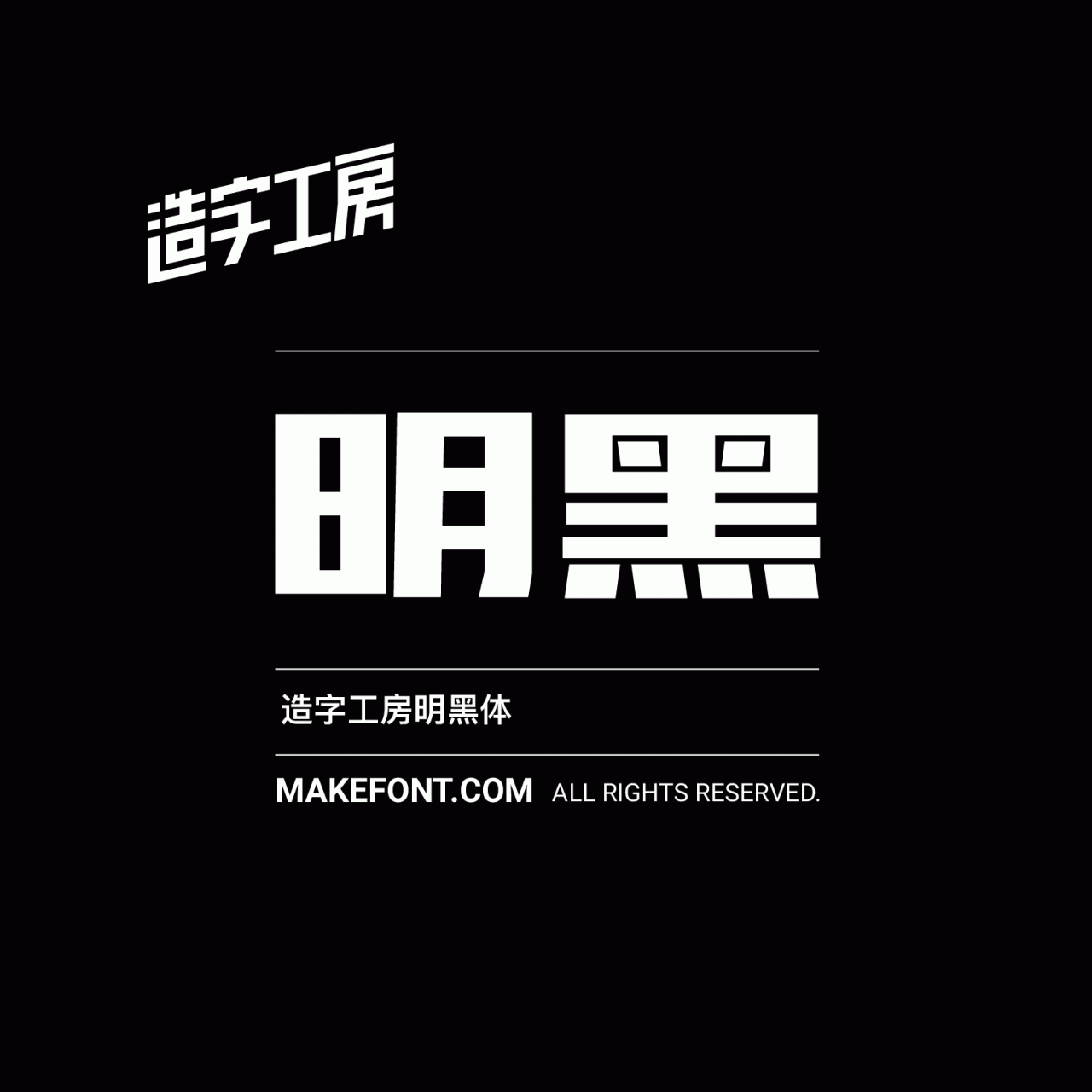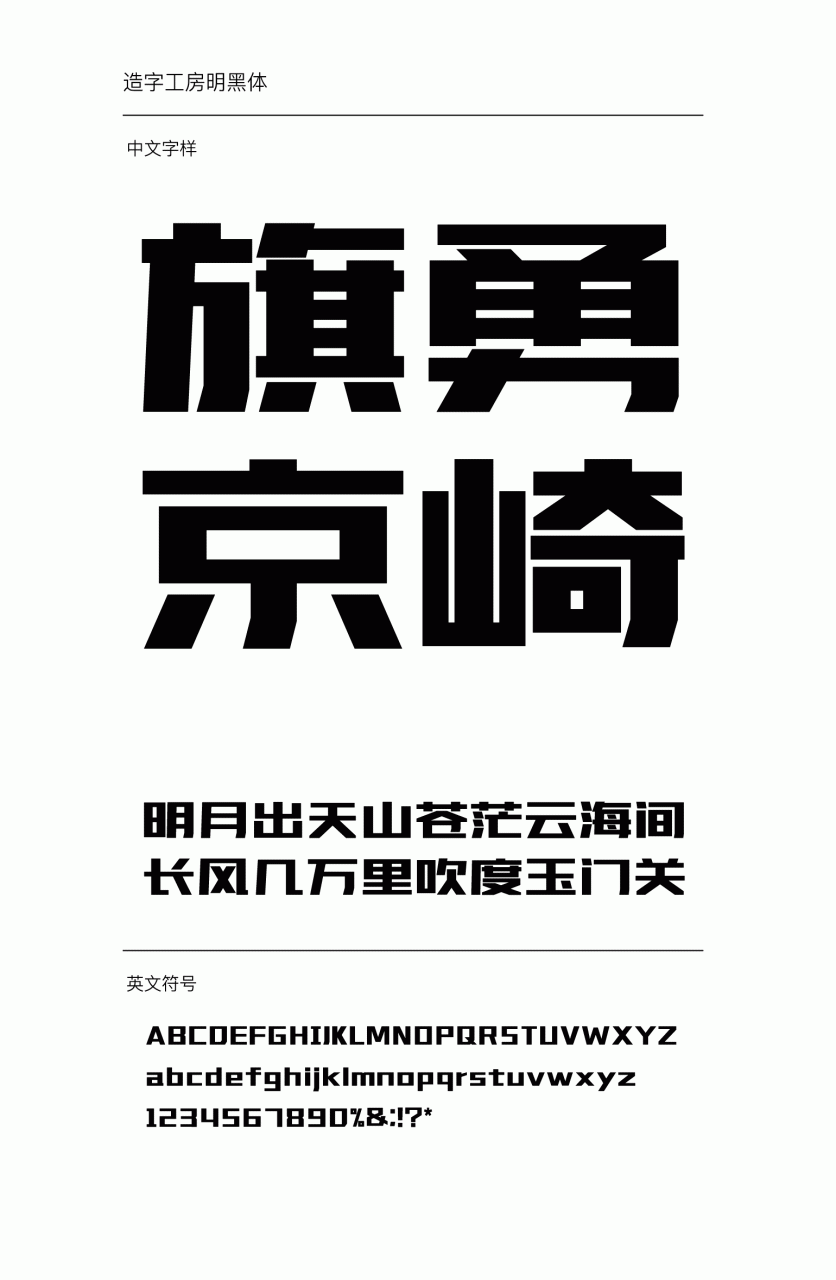
造字工房明黑常规体设计说明
造字工房明黑体字形扁平,笔画清晰而饱满,厚重工稳,遒劲有力,刚毅而不失俊朗,且直角的处理更显刚毅,有极强的视觉表现力。此款字体适用于主副标题,有着较大范围的应用空间。本字体为简体字库,采用OpenType/CID格式,Adobe-GB1-5编码。基于中华人民共和国GB2312-80字符集标准,另按需添加101个汉字。共收容字数6864CJK汉字,ASCII常用字符100个。